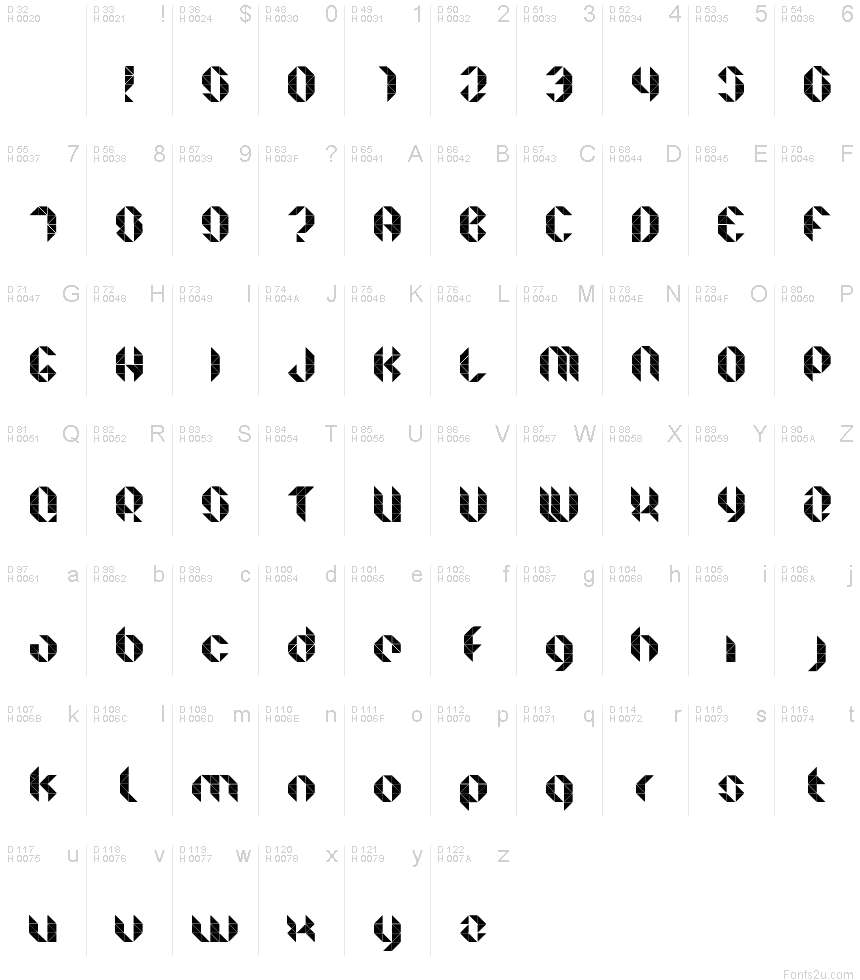
Facet Ultra 字体
Facet Ultra
Fontfabric
Svetoslav Simov
Facet Ultra 是一款由 Svetoslav Simov 为 Fontfabric 设计的免费数字显示字体。尖锐的三角形片段将字母分割成错落的平面,营造出一种类似折纸的几何律动感,极具未来气息。
其切割玻璃般的几何结构为品牌标识和专辑封面注入了动感,而这款免费字体则能为游戏标题和活动海报增添一种紧凑的工程质感。在科技产品包装和动态图形设计中,这些重复出现的切面可以将文字与网格、多边形以及其他数字元素完美连接。